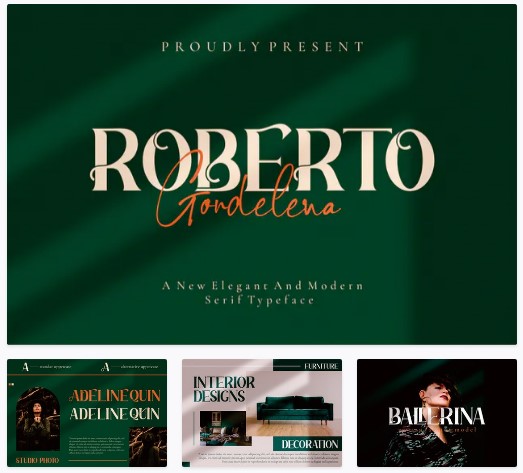
Elements.Envato Roberto & Gordelena Signature Font 2021
[Elements.Env ato] Roberto & Gordelena Signature Font (2021)
Roberto & Gordelena Signature - стильный дуо-лигатурный шрифт Display Serif, вдохновленный знаменитым минималистским логотипом, идеально подходит для целей дизайна шаблонов, брошюр, видео, рекламного брендинга, логотипов и многого другого.